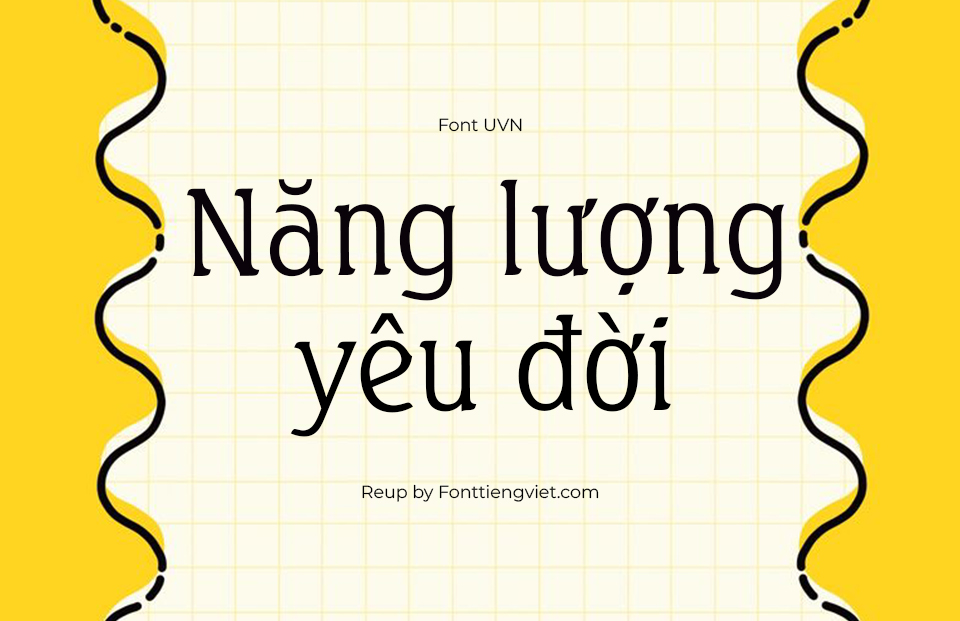
Tải Font Việt Hóa UVN Chim Bien Nhe Miễn Phí Cho Thiết Kế Giáo Dục
Giới thiệu về Font Việt Hóa UVN Chim Bien Nhe
Trong thế giới thiết kế đồ họa dành cho học đường, việc lựa chọn một bộ Font Chữ phù hợp đóng vai trò quan trọng trong việc truyền tải kiến thức. Font Việt Hóa UVN Chim Bien Nhe là một trong những kiểu chữ thuộc bộ sưu tập UVN nổi tiếng, được tinh chỉnh để hiển thị tiếng Việt một cách hoàn hảo nhất. Với nét chữ thanh mảnh, nhẹ nhàng và bay bổng như tên gọi của nó, bộ font này mang lại cảm giác dễ chịu, gần gũi cho người đọc, đặc biệt là các bạn học sinh và giáo viên trong quá trình soạn thảo giáo án hay trình chiếu bài giảng.
Đặc điểm nổi bật của kiểu chữ
Đặc trưng lớn nhất của Font Việt Hóa UVN Chim Bien Nhe chính là sự thanh thoát trong từng đường nét. Không giống như các phông chữ kỹ thuật khô khan, Chim Biển Nhẹ sở hữu những đường cong mềm mại, tạo nên một tổng thể hài hòa và tinh tế. Font chữ này hỗ trợ đầy đủ bảng mã Unicode, giúp người dùng không còn lo lắng về lỗi font khi gõ các ký tự có dấu phức tạp trong tiếng Việt. Đây là lựa chọn lý tưởng cho các biểu mẫu khen thưởng hoặc trang trí bìa sách giáo khoa.
Ứng dụng thực tế và cách cài đặt
Lưu ý khi sử dụng trong học tập
Dù mang tính thẩm mỹ cao, người dùng nên kết hợp bộ font này với các font không chân khác để đảm bảo tính dễ đọc cho những đoạn văn bản dài. Sự kết hợp thông minh sẽ giúp sản phẩm thiết kế vừa đẹp mắt vừa chuyên nghiệp.
Kết luận về bộ font chữ đẹp